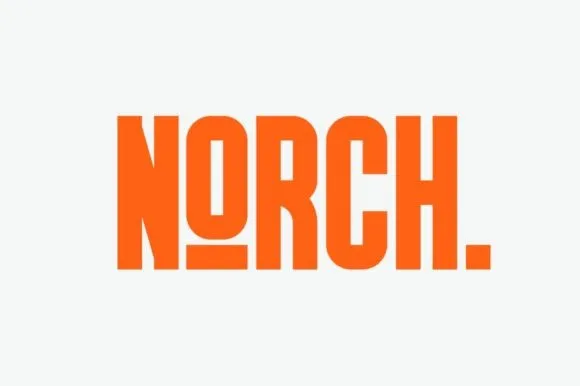
A Norch Sans Serif é uma nova escolha moderna para qualquer designer gráfico que busca uma tipografia sem serif poderosa e versátil. Disponível tanto para títulos e headlines quanto para projetos variados, esta fonte foi desenvolvida pelo Garisman Studio. Com um design simples e casual, a Norch oferece uma aparência limpa e elegante devido à sua organização meticulosa das letras. Esta tipografia destaca-se em ambientes tanto formais quanto informais, proporcionando um visual impecável para seus trabalhos. É especialmente adequada para projetos visuais como cartazes, gráficos e logotipos que precisam de tipografia forte e impactante. Norch não é apenas uma fonte elegante para uso em títulos e headlines; também oferece o conforto e a simplicidade necessários para projetos mais detalhados. É um ótimo complemento para qualquer trabalho gráfico, trazendo ao seu projeto um visual moderno e profissional.